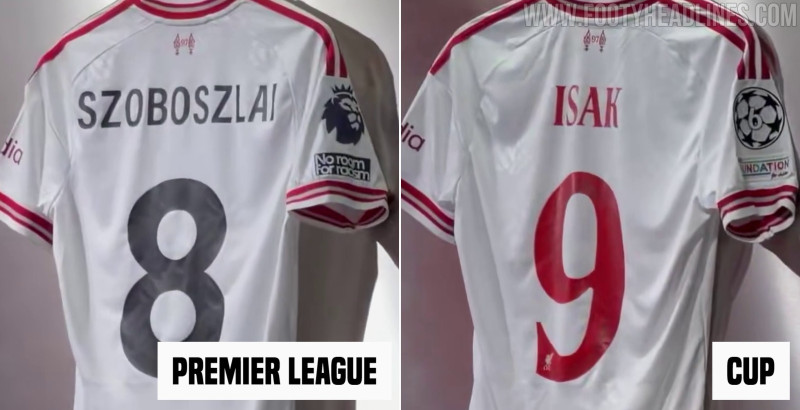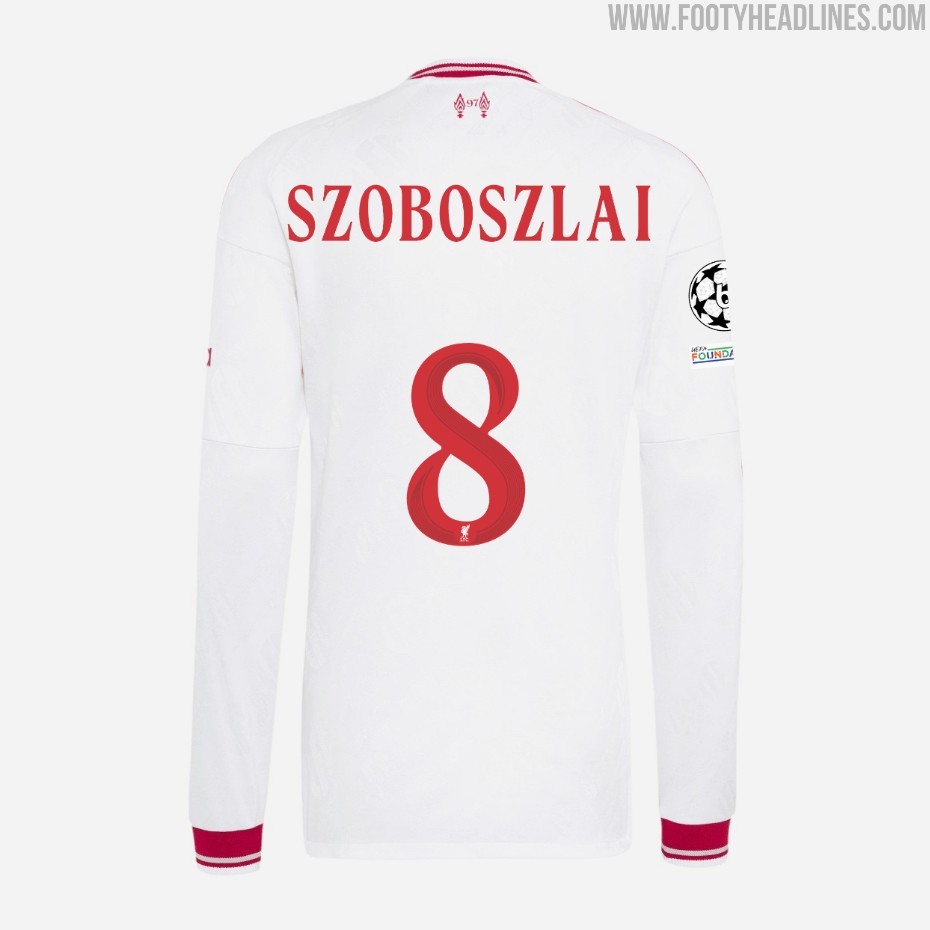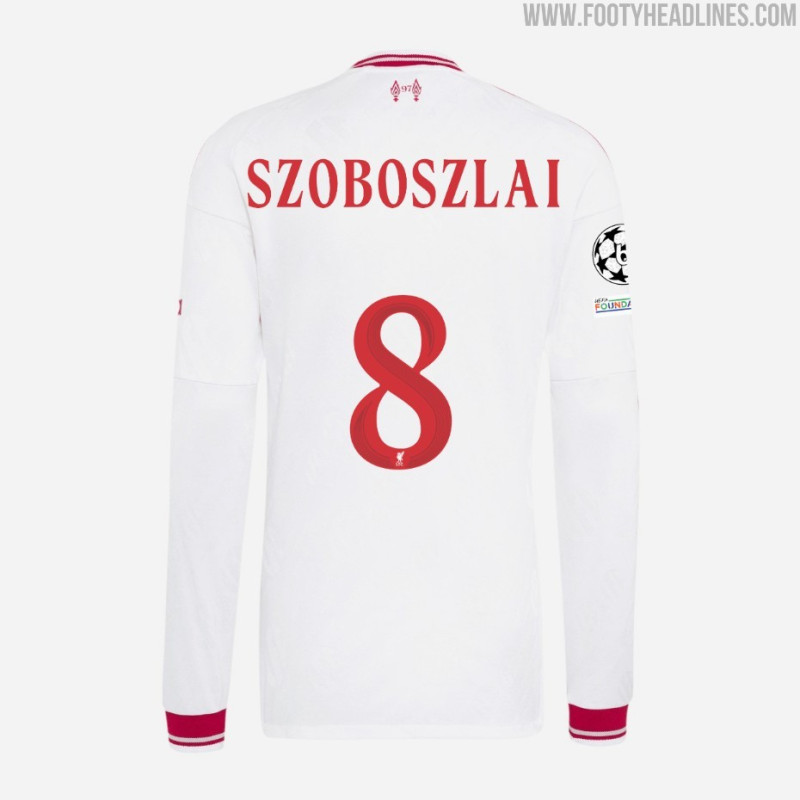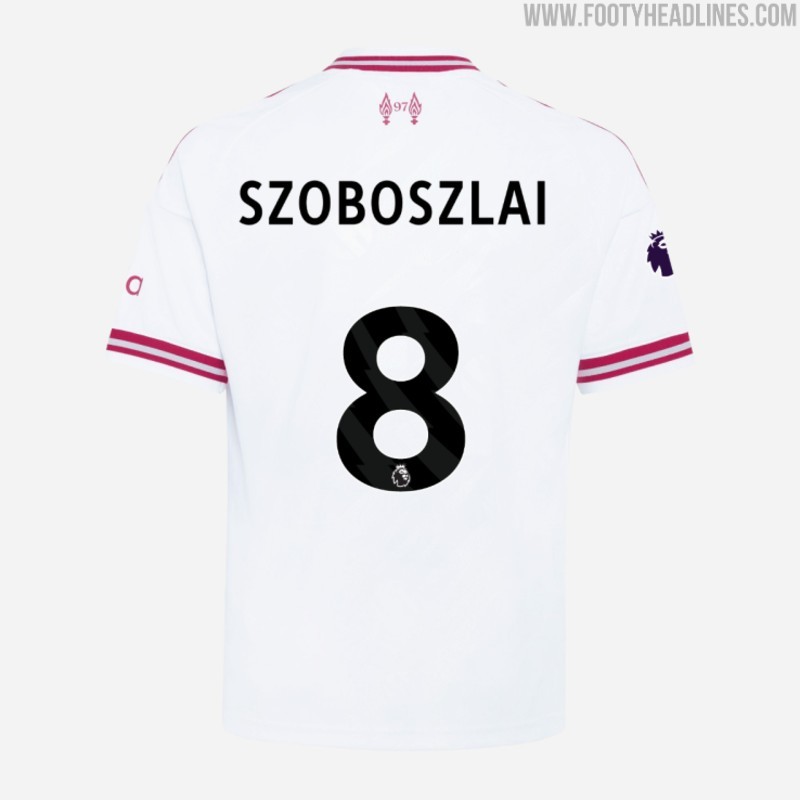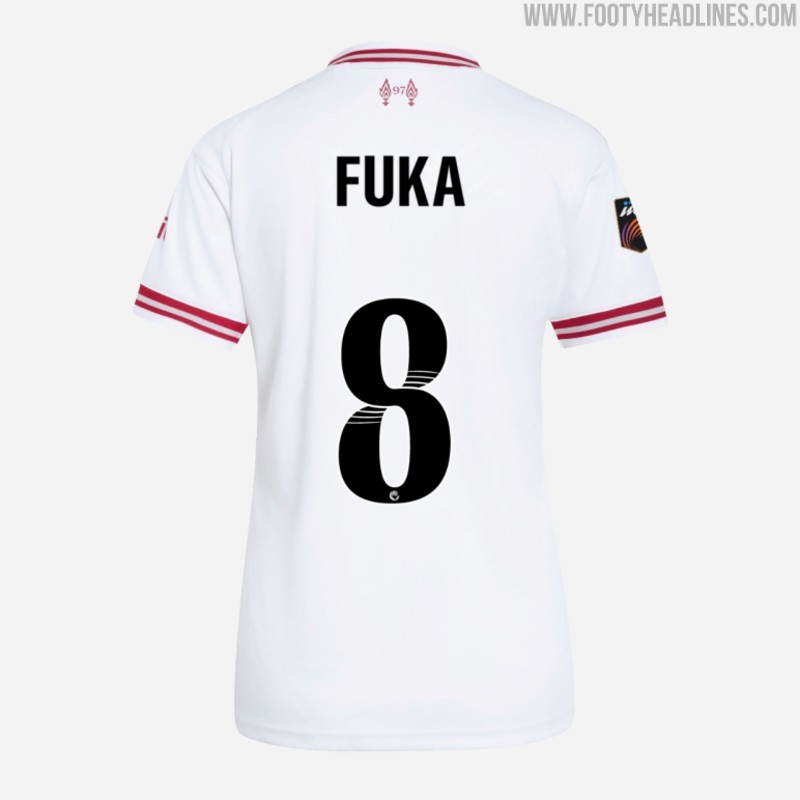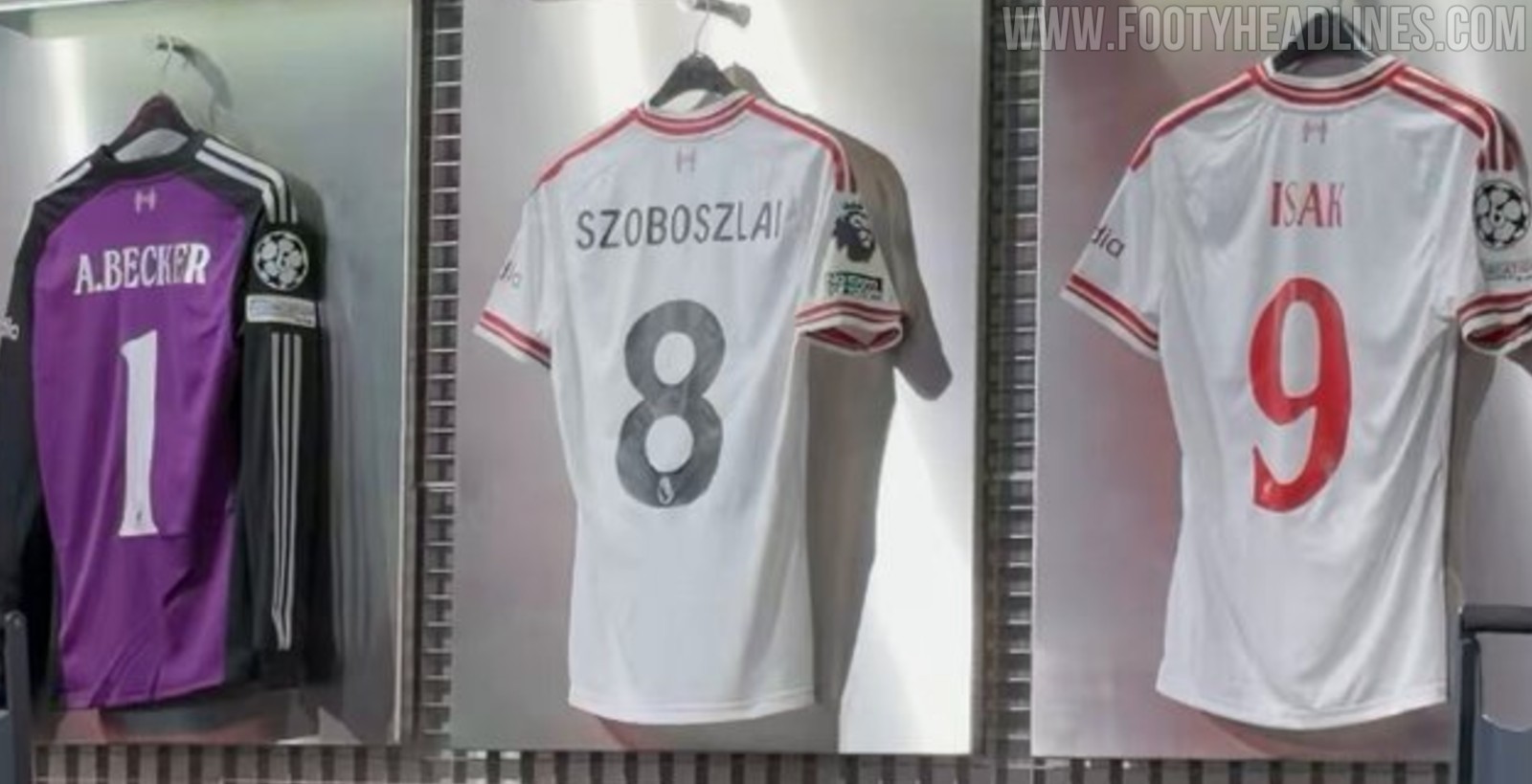
La camiseta visitante del Liverpool de la temporada 26-27 lleva la tipografía negra de la Premier League
• Presentación y Diseño Oficial: El Liverpool ha presentado oficialmente su camiseta visitante retro de la temporada 26-27, diseñada por Adidas, que combina el clásico logotipo del trébol con el escudo tradicional del 'Liver Bird' de los años 80.
• Tipografía de la Premier League: Para los partidos de la Premier League, la camiseta visitante del Liverpool 26-27 llevará letras y números negros en la espalda, en lugar de rojos, posiblemente para evitar un desajuste en el tono del rojo.
• Tipografía para Partidos de Copa: En los partidos de copa, el Liverpool usará su nueva tipografía de copa en un rojo a juego, la cual incluye el logotipo moderno del Liverbird con las letras 'LFC', a pesar de que la camiseta lleva el escudo clásico.
El Liverpool ha presentado oficialmente su camiseta visitante para la temporada 26-27, de inspiración retro, diseñada por Adidas y que luce el clásico logotipo del trébol junto con el escudo tradicional del «Liver Bird» de los años 80. La elección de los colores de la tipografía ha sorprendido a muchos; gracias a ++Jay Pearson++, de Tops of the Kop, por el detalle.
El diseño de la camiseta visitante del Liverpool 26-27 presenta un fondo blanco roto resaltado por llamativos detalles en rojo en el cuello, las rayas de los hombros y los puños de las mangas. Solo hay estos dos colores, además del gris para los detalles. Sin embargo, la camiseta contará con un cuarto color en el campo durante los partidos de liga.
Para los partidos de la Premier League, la camiseta visitante del Liverpool para la temporada 2026-2027 lleva letras y números negros en la espalda, y no los rojos que aparecen en una de las 5 opciones predeterminadas. Probablemente sea porque la tipografía roja simplificada de la EPL tiene un tono de rojo diferente al de la camiseta. La versión de la WSL también lleva tipografía negra.
En los partidos de copa, el Liverpool usará su nueva tipografía de copa, en un rojo a juego. Curiosamente, la tipografía viene con el logotipo habitual del Liverbird con las letras «LFC», aunque la camiseta lleve el clásico.